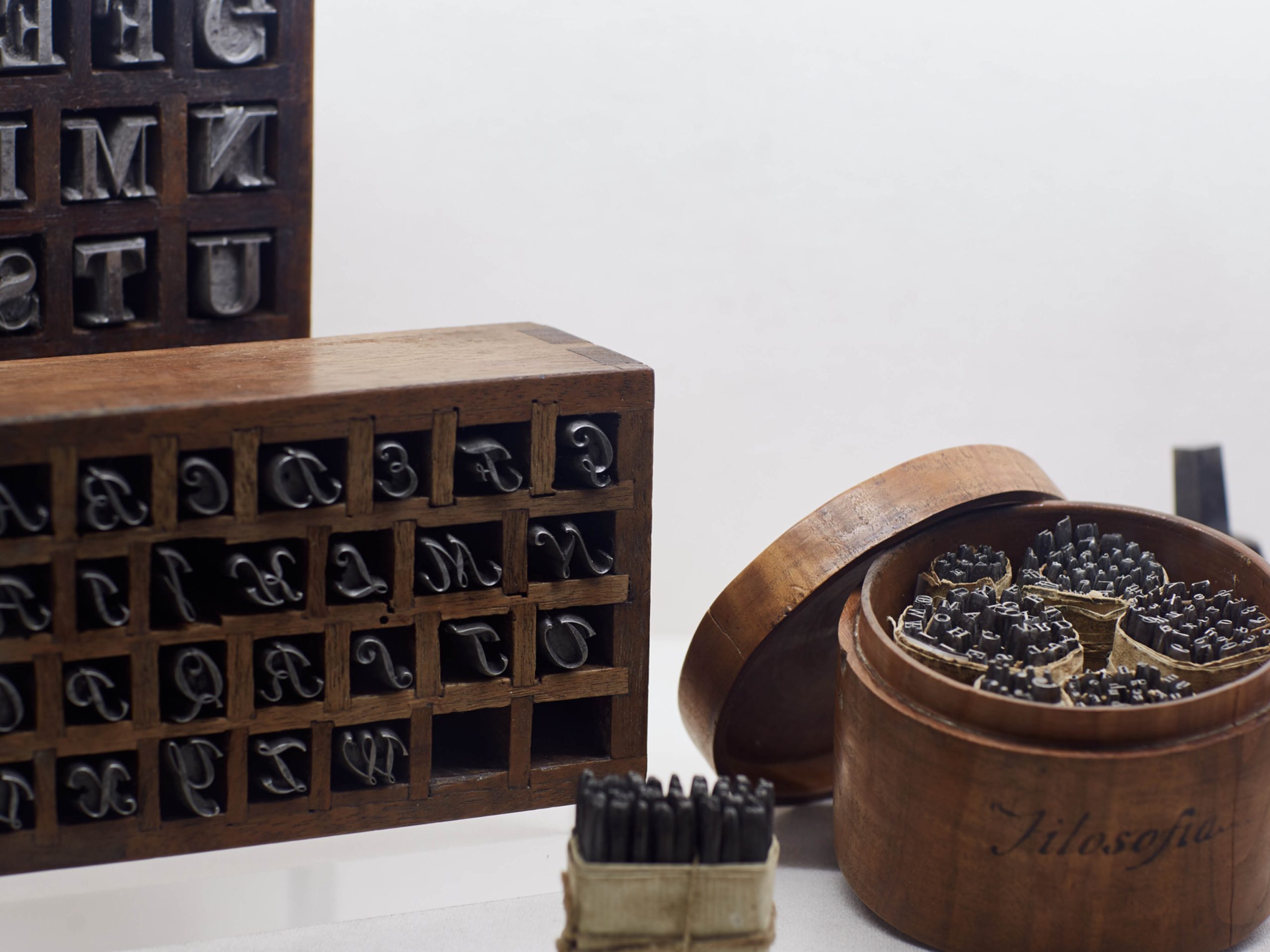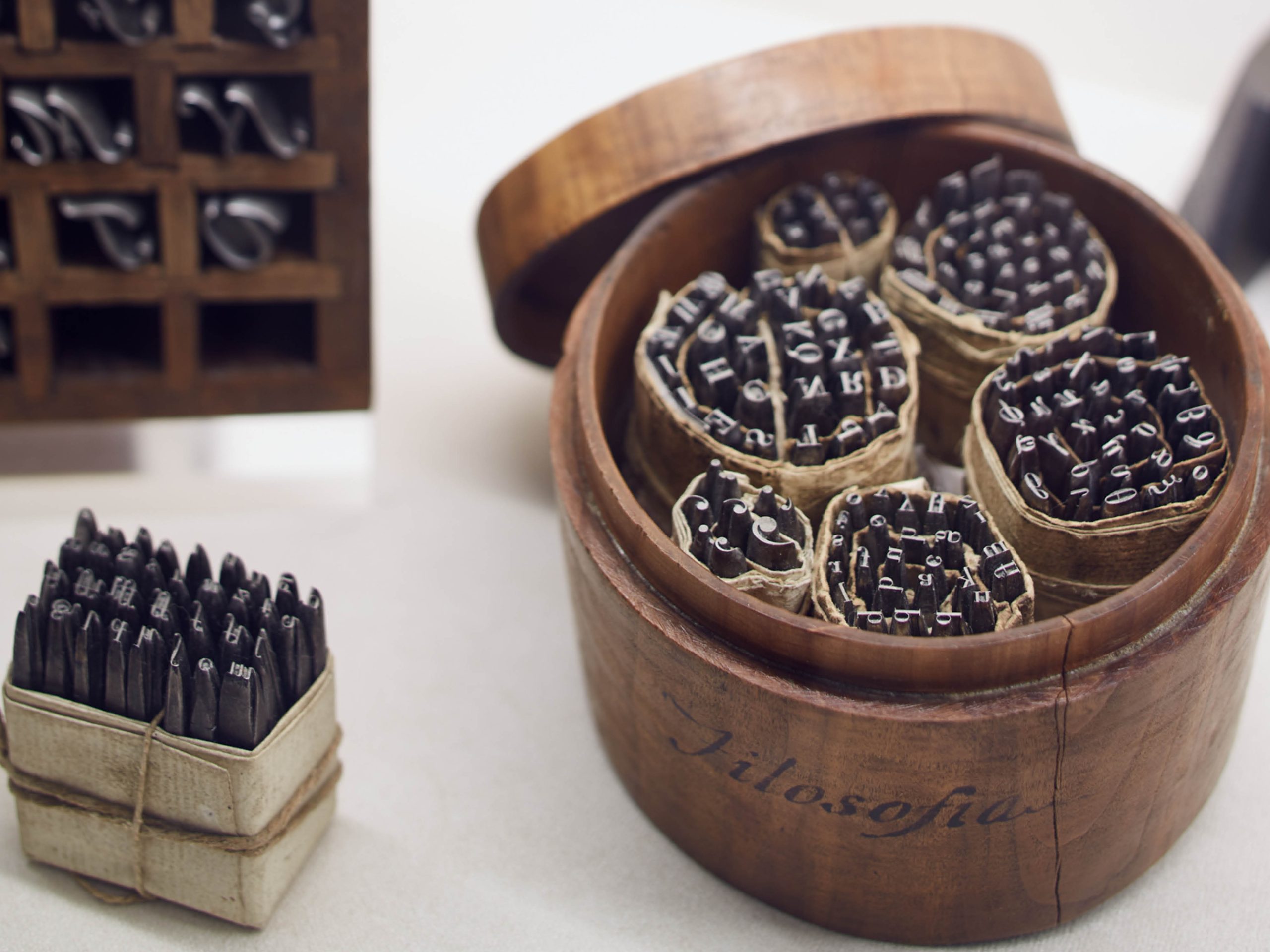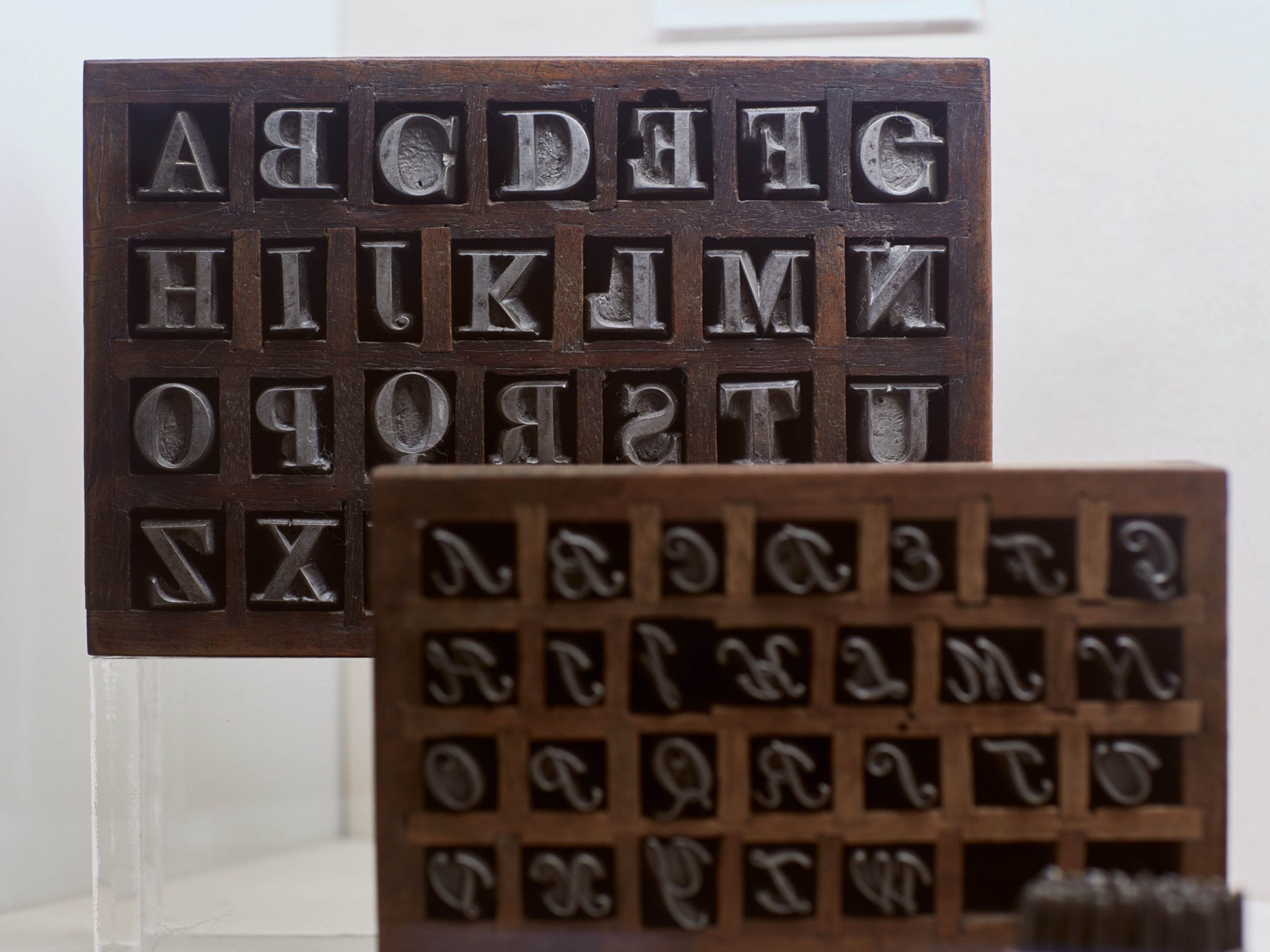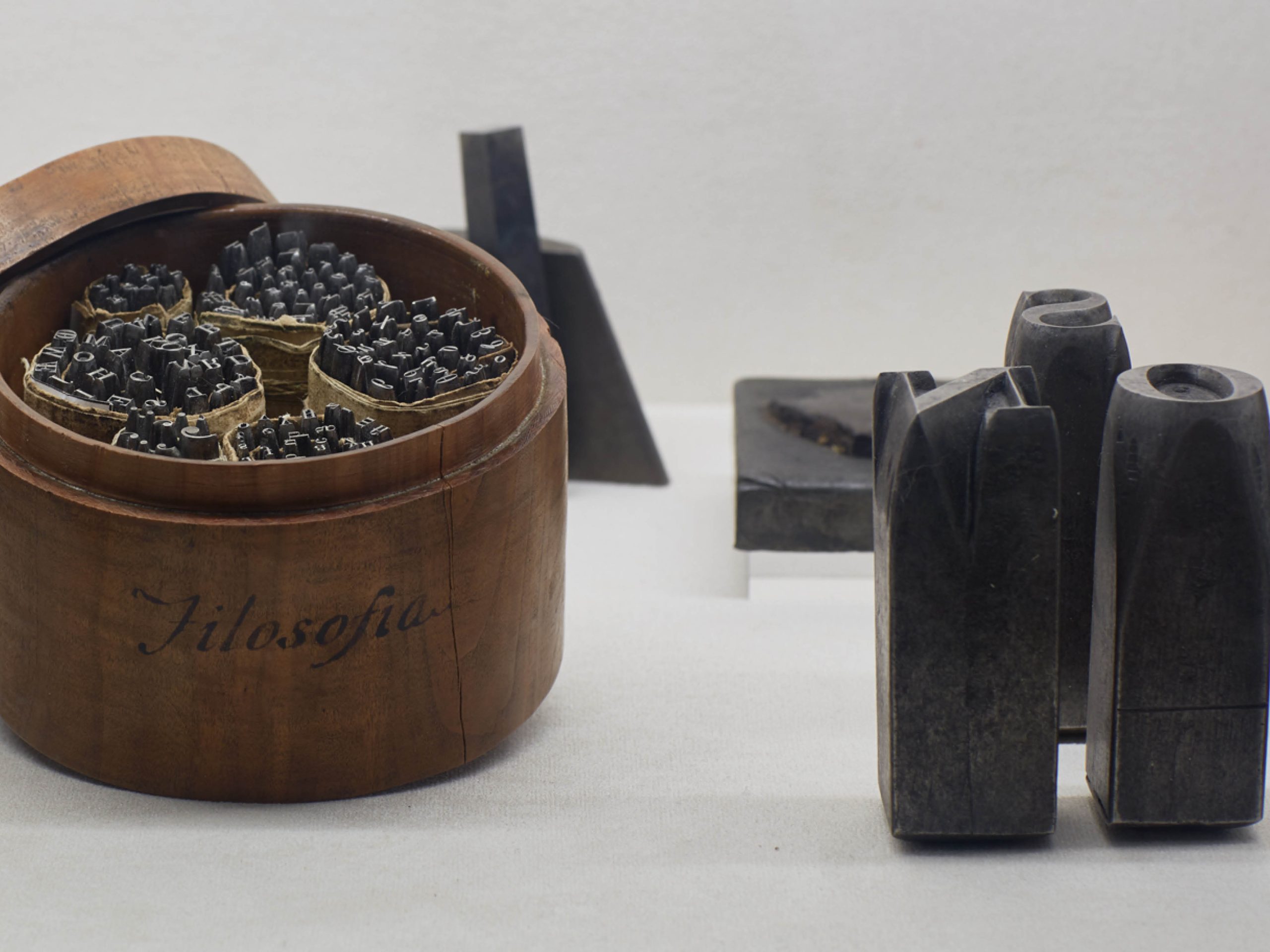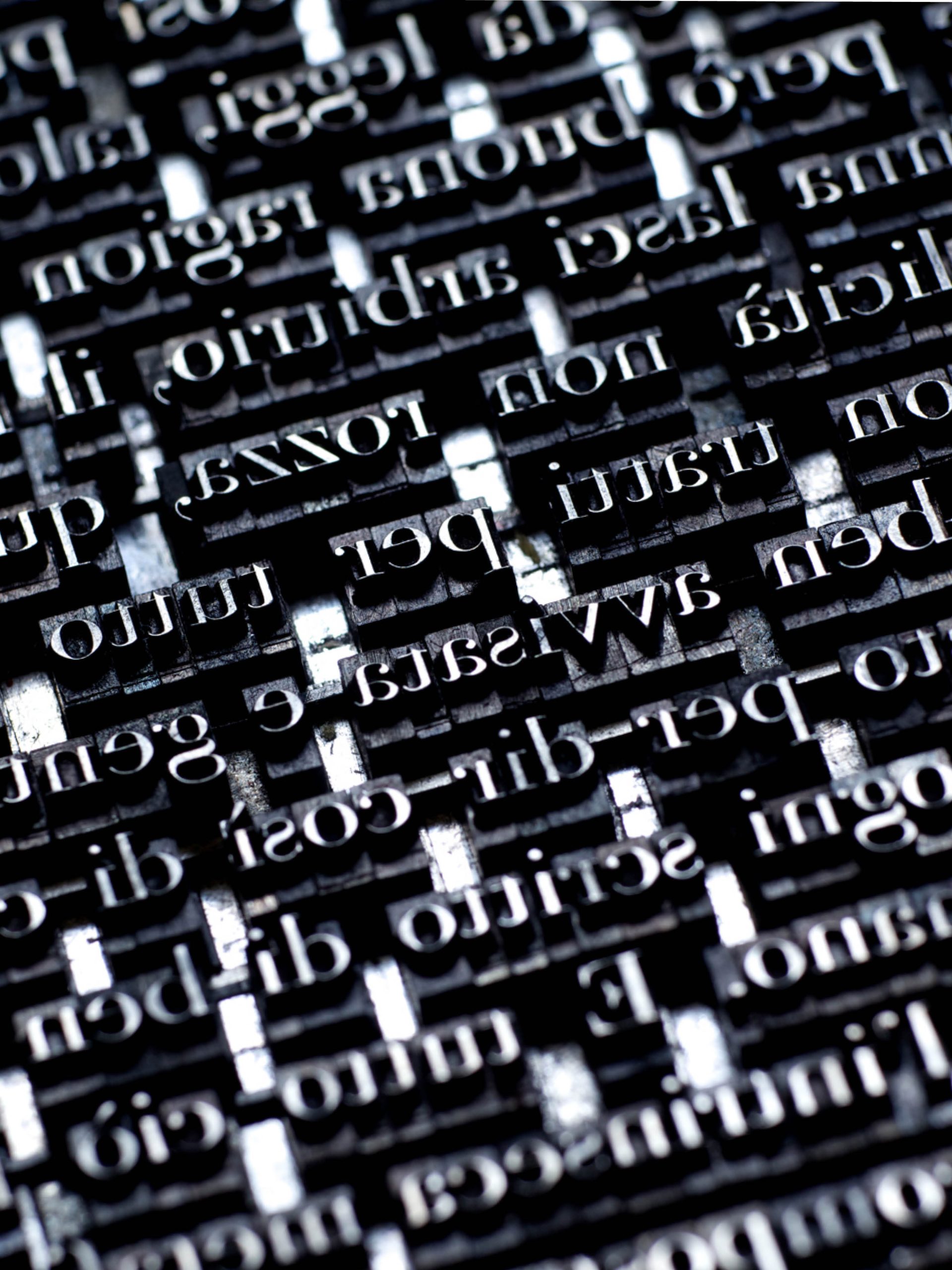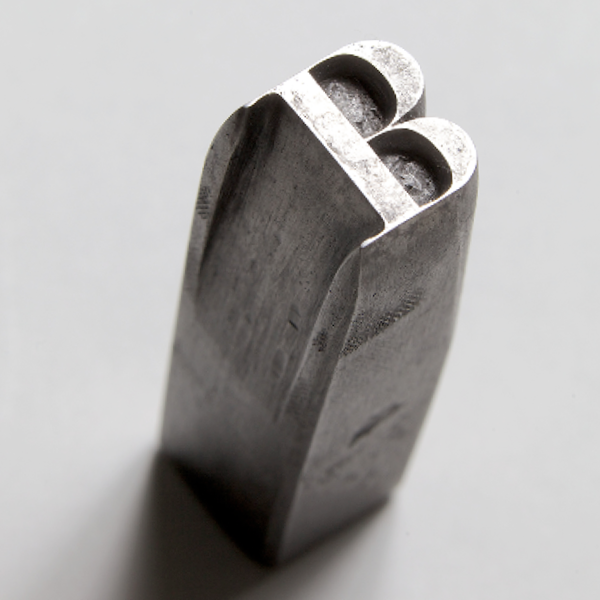
Giambattista Bodoni
Forse il nome Bodoni risulta familiare perché associato a un carattere tipografico. A dire il vero, è uno dei caratteri italiani più celebri. Ma, ancor prima, Bodoni è il cognome di uno dei protagonisti assoluti della tipografia italiana, un nome famoso in tutto il mondo. Ancora oggi, il carattere Bodoni esprime aristocratica eleganza e nobile grazia, e continua a vivere anche come font digitale in bella vista sulle riviste di moda o in eleganti edizioni di lusso. Giambattista Bodoni nasce a Saluzzo, in Piemonte, nel 1740 ma la sua fama si lega indissolubilmente alla città di Parma, dove creò la Stamperia Reale, con la collaborazione anche dei fratelli Amoretti, di cui Tipoteca conserva i preziosi punzoni con i quali si incidevano le matrici per la fusione. Bodoni è un vero fuoriclasse, da molti considerato il “principe dei tipografi”. A Parma ha lasciato un patrimonio di punzoni, caratteri, edizioni sontuose e di raffinata eleganza. E pensare che, in quel tempo, tutto doveva essere fatto a mano: l’incisione dei punzoni, la fusione dei caratteri, la composizione e la stampa al torchio. Bodoni è ricordato, in particolare, per il Manuale tipografico, pubblicato postumo dalla vedova nel 1818 (Bodoni muore nel 1813). II Manuale è considerato un monumento della tipografia neoclassica, arricchito non solo dai caratteri latini, ma da tanti caratteri “esotici” (oggi, sono definiti non latini) come il greco, il cirillico, l’ebraico, l’arabo, l’armeno… Bodoni era un vero appassionato di questi alfabeti, che ebbe modo di apprendere da giovane quando ebbe un incarico a Roma alla Propaganda Fide.